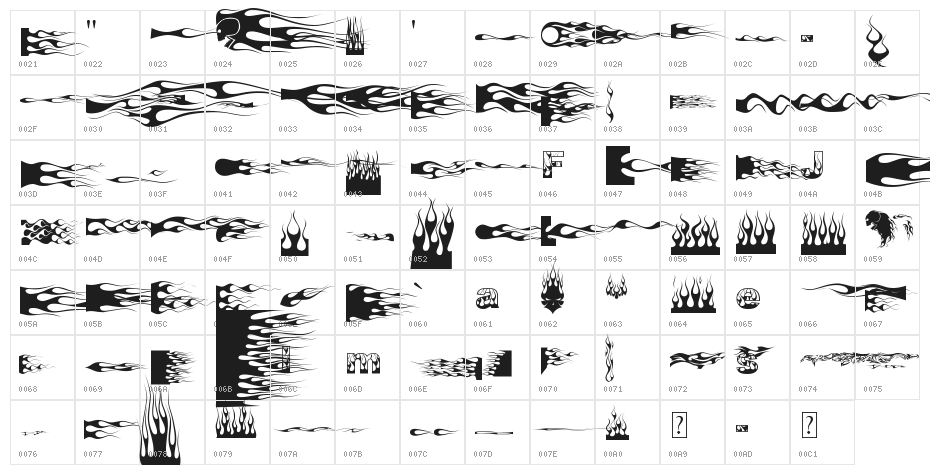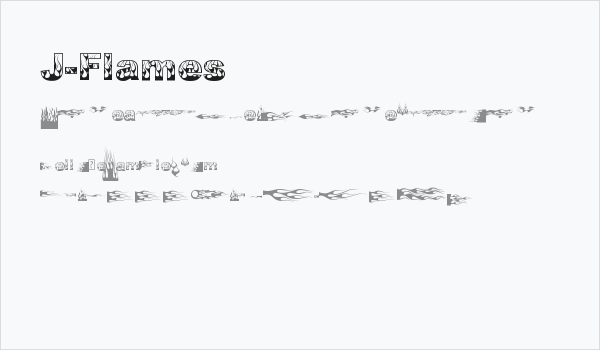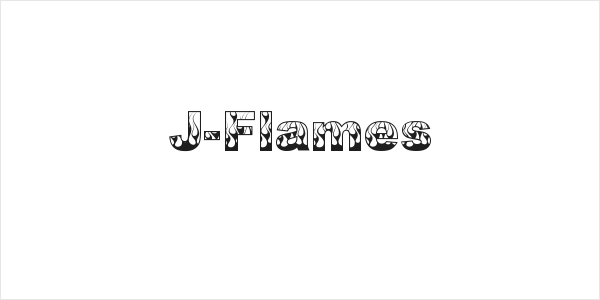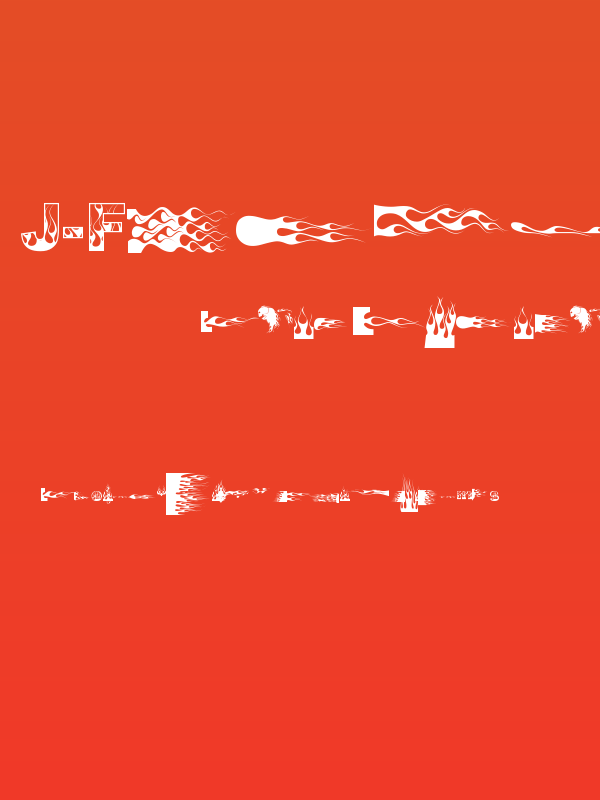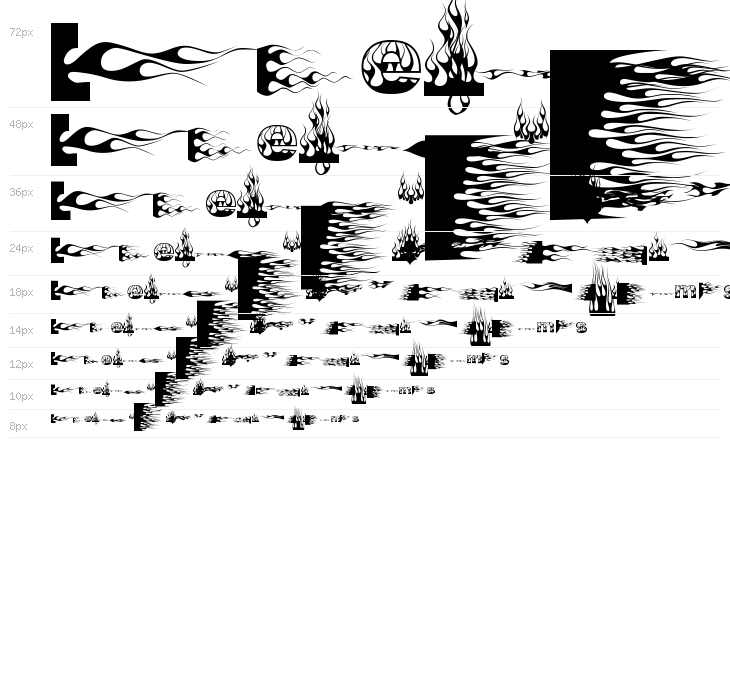
J-Flames Font
| Vorgeschlagene Projekte | Ideal for use in posters, album covers, event flyers, and branding for extreme sports or entertainment industries. |